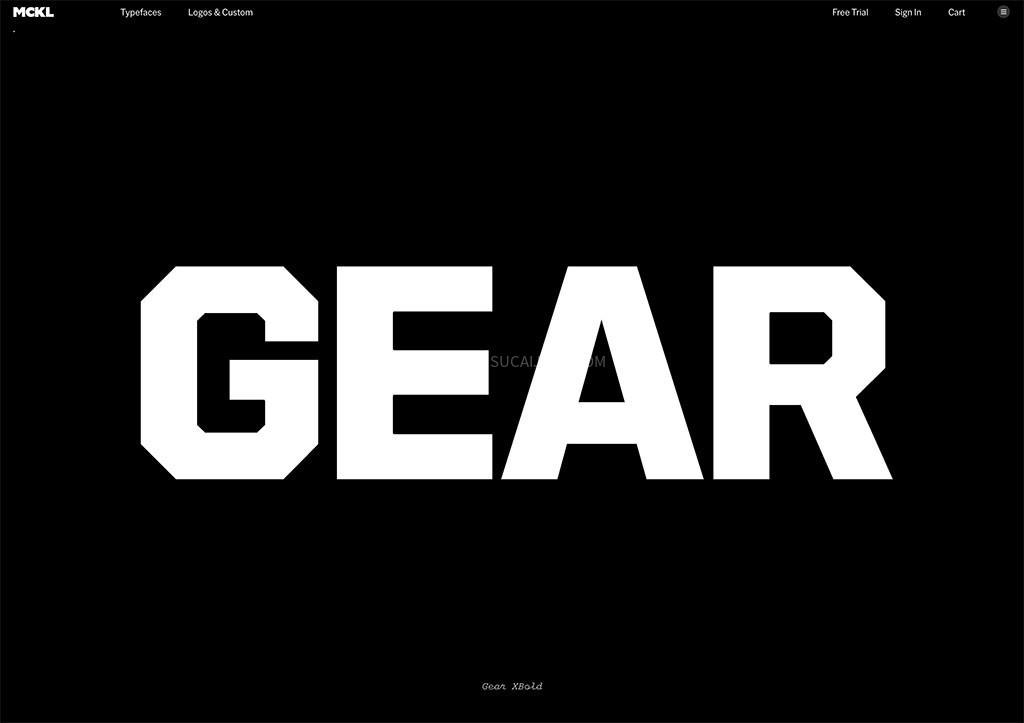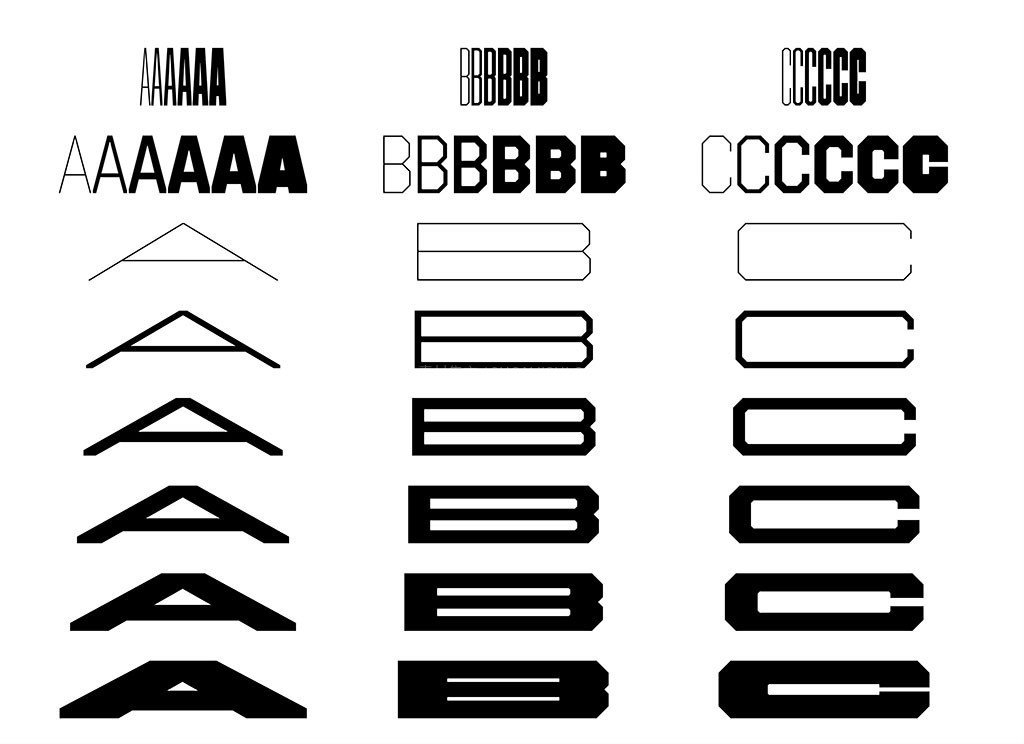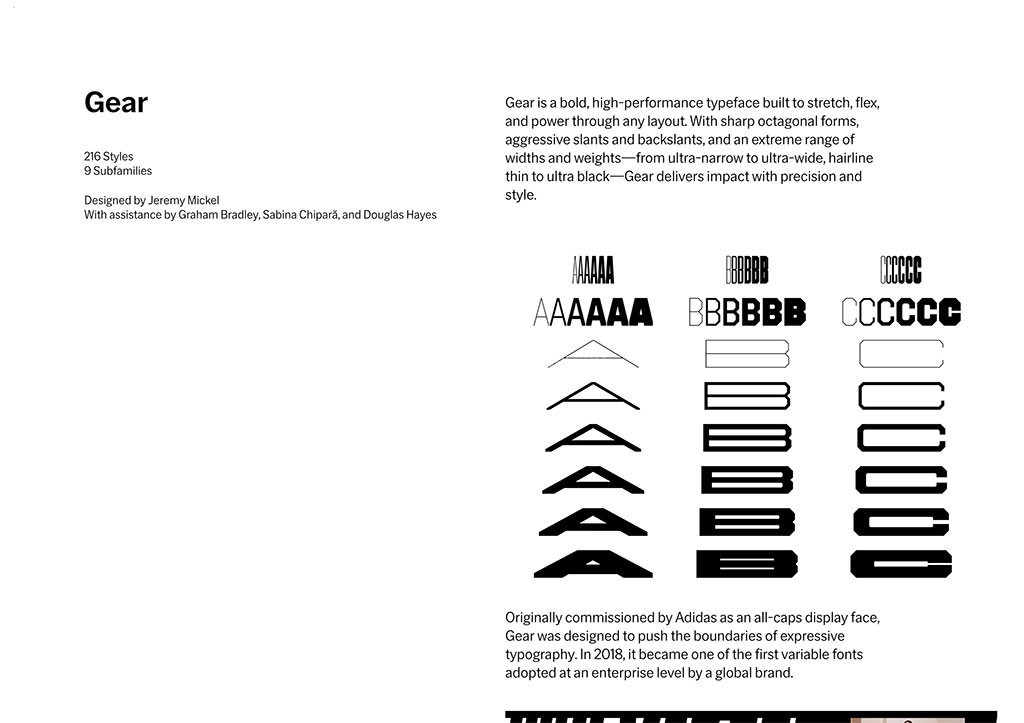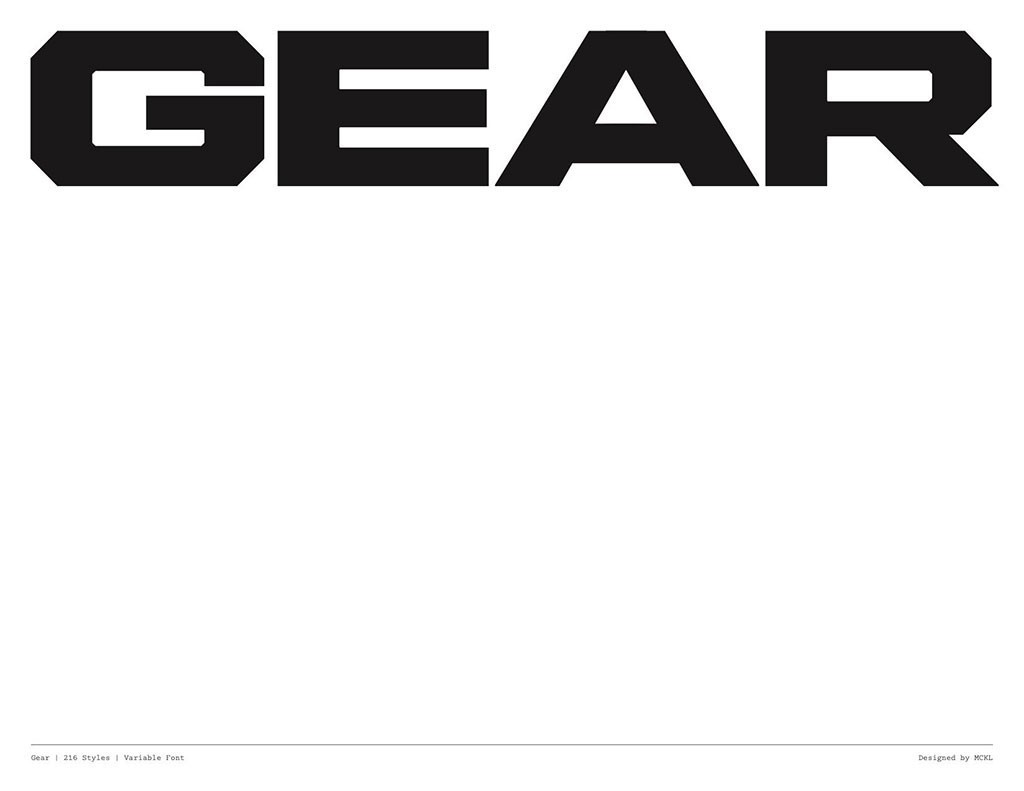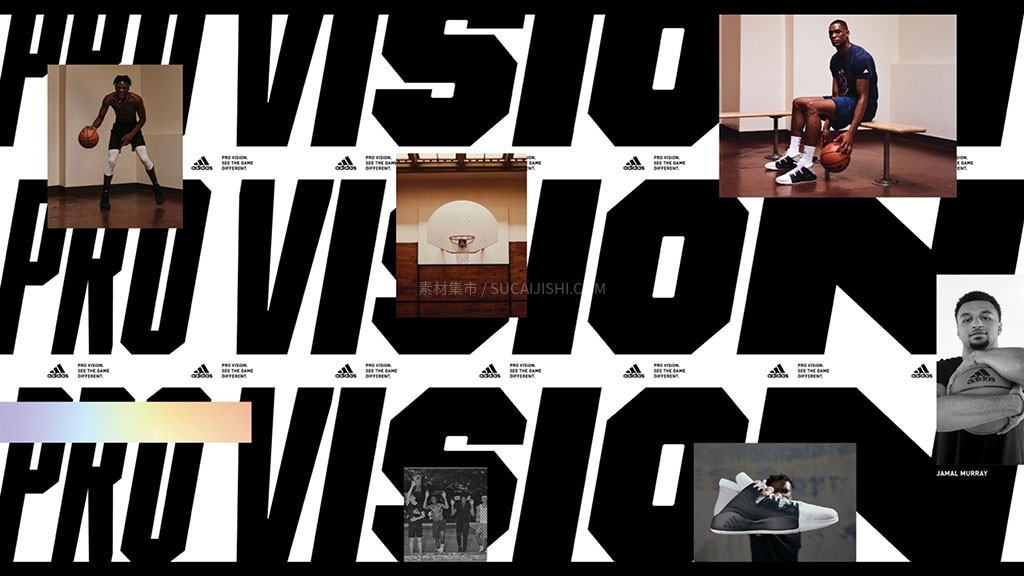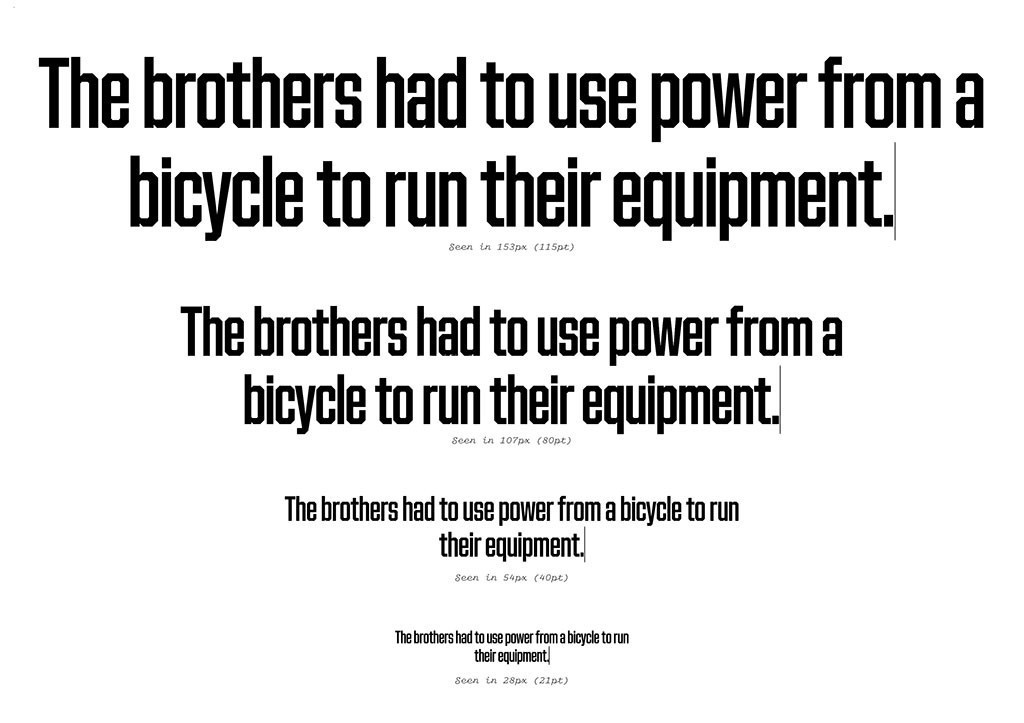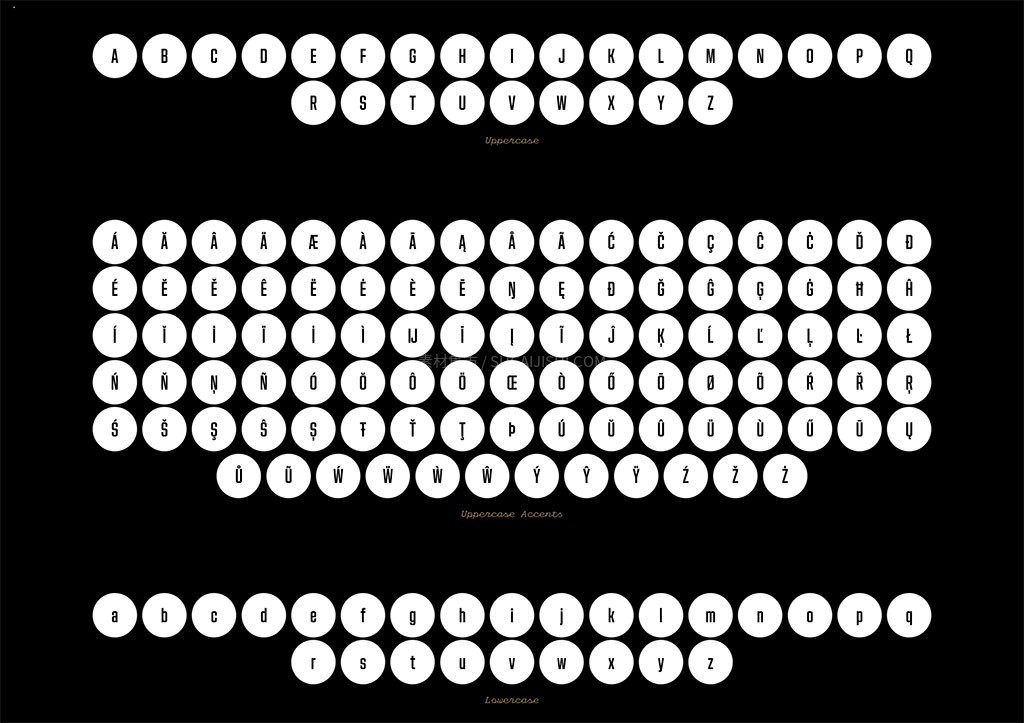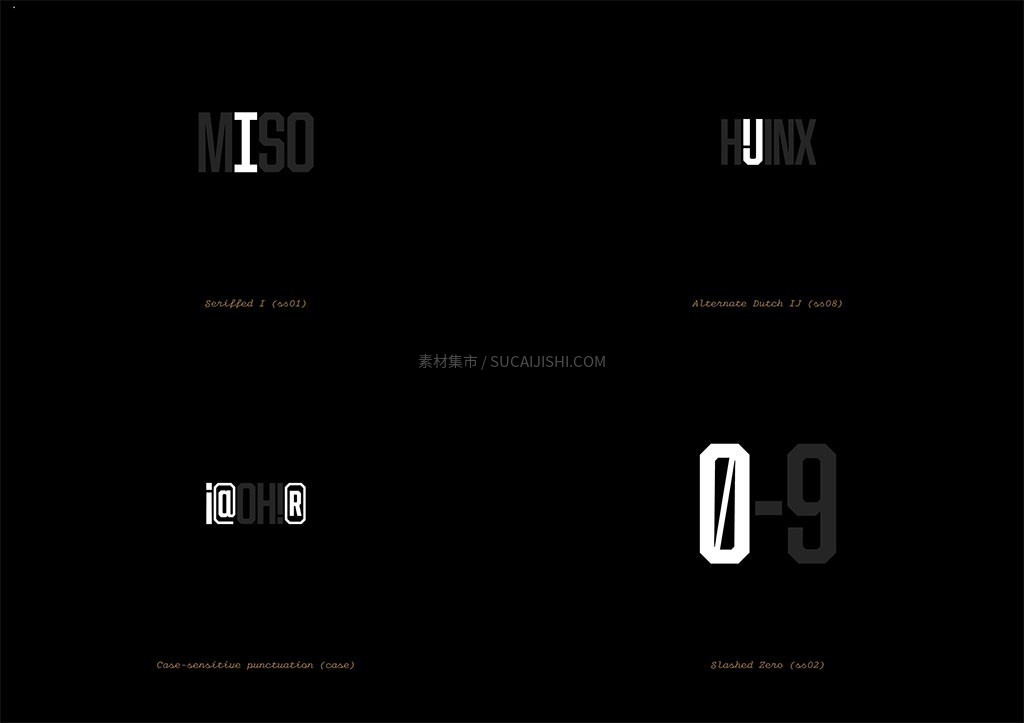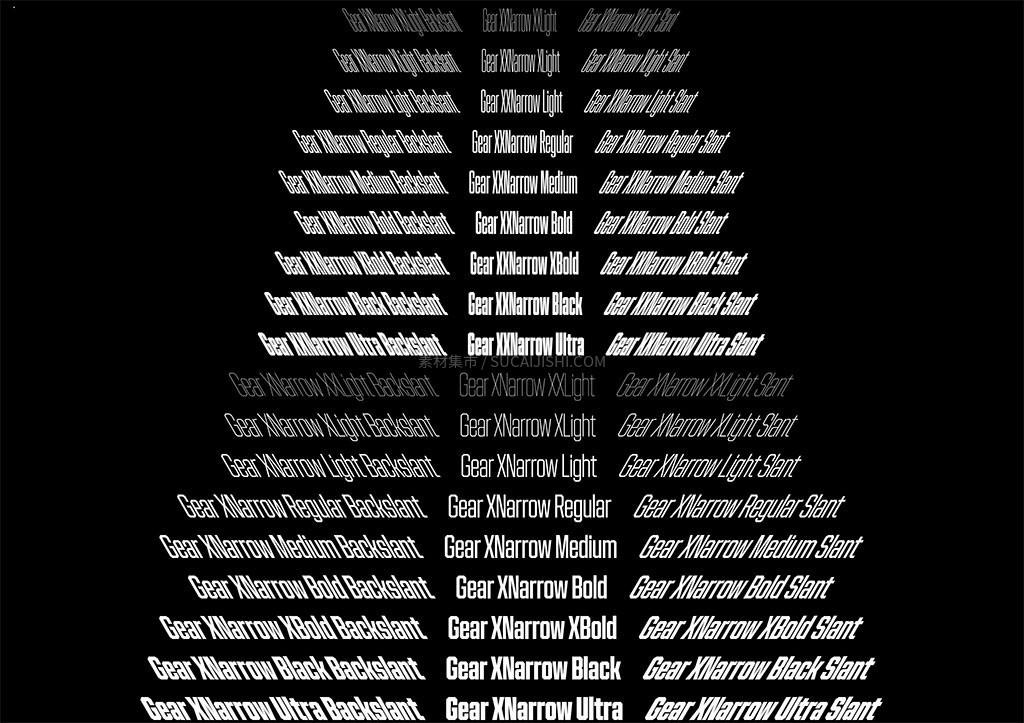
Gear SuperFamily 高性能字体家族
Gear 是一款大胆且高性能的超级字体系统,旨在灵活适应各种版式并展现强大的视觉气场。它拥有锐利的八边形轮廓,系统内包含完整的小写字母集以及经过优化的字形与比例。全套字体涵盖了从极窄到极宽、从极细到极黑的丰富设定,并提供直立、斜体与反斜体三种角度。同时,Gear 还支持作为可变字体使用,实现所有轴上的平滑插值,是打造空间填充排版与自适应设计的强大工具。